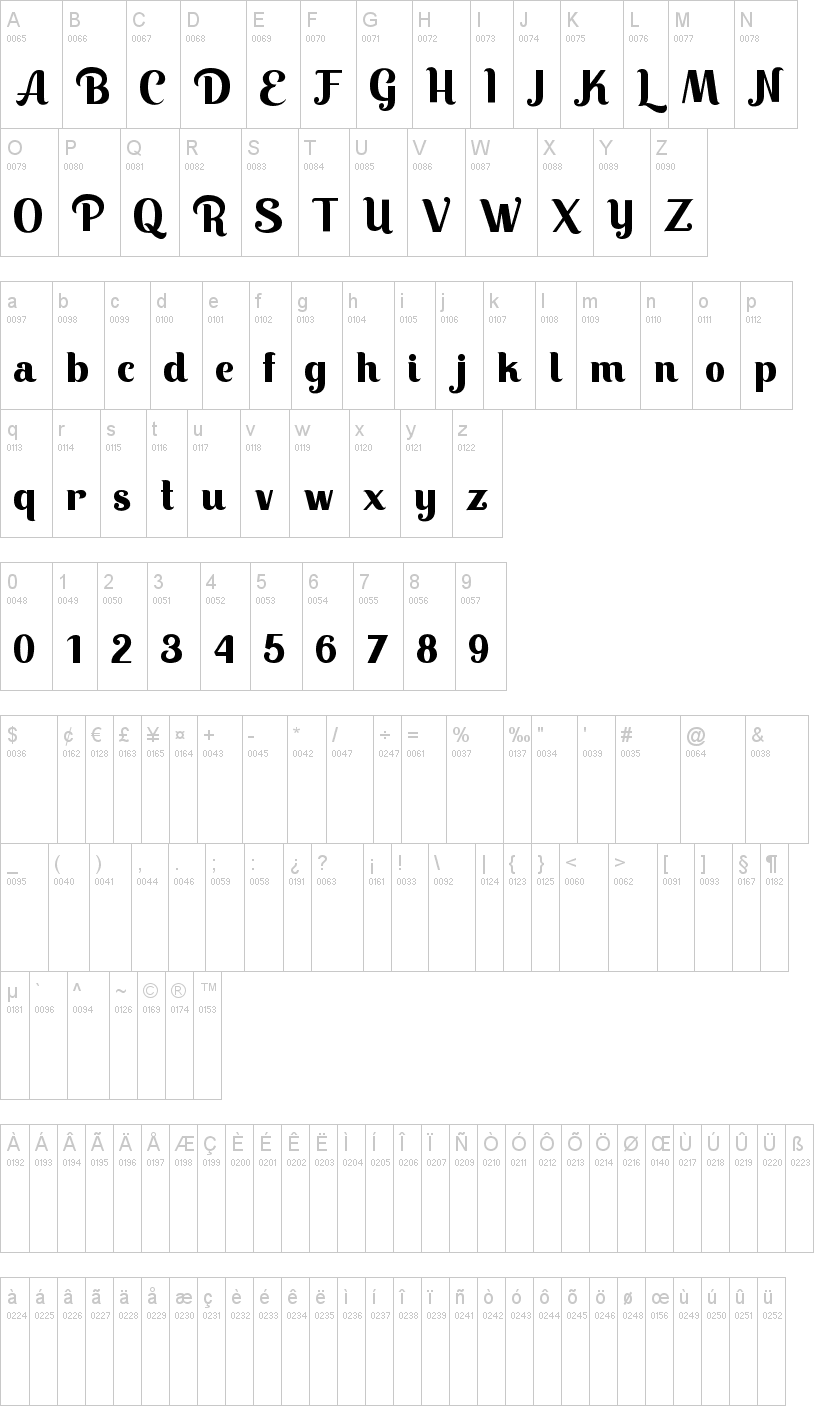
Keilla
Keilla 字体是一种清新活泼的草书字体,由著名的设计师 Kiel Mutschelknaus 创造。它拥有细腻的线条和流畅的曲线,特别适合用于报纸,杂志,海报,书籍,电视和电影标题等。它的特点是简洁明了,字形结构完整,更加灵活,让您的文字更加生动有趣。
Keilla是一款非常不错的手写艺术字体,具有很好的视觉感,适合于文化类的宣传设计、商业类品牌的广告和产品包装设计以及个性化文字排版等较多场景。